В 2026 году выбор шрифта для сайта в России — это уже не только вопрос дизайна. На практике нужно одновременно учитывать три фактора: законность использования, качество кириллицы и устойчивость канала доступа к самой гарнитуре. Ошибки обычно возникают не из-за названия шрифта, а из-за способа его применения: без лицензии, вне условий лицензии, через незаконный self-hosting или через зависимость от поставщика, с которым для российских компаний возможны ограничения на покупку и сопровождение.
Для веб-проектов поэтому важно разделять три группы: безопасные шрифты, шрифты с лицензионными рисками и шрифты с санкционно-операционными рисками для России. Ниже — практический разбор именно в этой логике.
Безопасные шрифты
Самый надежный выбор для сайта в России в 2026 году — открытые шрифты с прозрачной лицензией, понятным происхождением и качественной кириллицей. В этом смысле сильной базой остается каталог Google Fonts: сервис прямо указывает, что все шрифты в каталоге open source, доступны для использования в цифровых проектах, а также поддерживаются с точки зрения и веб-доставки. Для веб-разработки это означает предсказуемый сценарий: понятная лицензия, понятный источник и отсутствие необходимости отдельно покупать коммерческую webfont-лицензию у классической шрифтовой платформы.
Inter
Inter — один из самых безопасных и практичных вариантов для современных интерфейсов, сервисов и корпоративных сайтов. Официальное описание Google Fonts говорит, что гарнитура специально спроектирована для экранов, а официальный репозиторий Inter указывает лицензию SIL Open Font License 1.1. Это делает Inter удачным базовым шрифтом для продуктовых интерфейсов, лендингов, личных кабинетов, SaaS-сервисов и контентных платформ.
Manrope
Manrope — еще один безопасный выбор для веба. Google Fonts прямо описывает его как open-source modern sans serif, а в официальном репозитории указана та же лицензия SIL Open Font License 1.1. Для российского рынка он удобен тем, что сочетает современный нейтральный рисунок с поддержкой кириллицы и не создает лишней зависимости от коммерческих каналов лицензирования.
Golos Text
Golos Text — особенно уместный вариант для русскоязычных проектов. Google Fonts описывает его как гарнитуру, созданную для государственных и социальных сайтов и хорошо подходящую для непрерывного чтения с экрана. В официальном репозитории Golos Text также указана лицензия SIL Open Font License 1.1. Для сайтов на русском языке это один из самых рациональных вариантов: кириллица была в фокусе проекта с самого начала, а сам шрифт хорошо подходит для длинных текстов, интерфейсов и сервисных сценариев.
Пример:
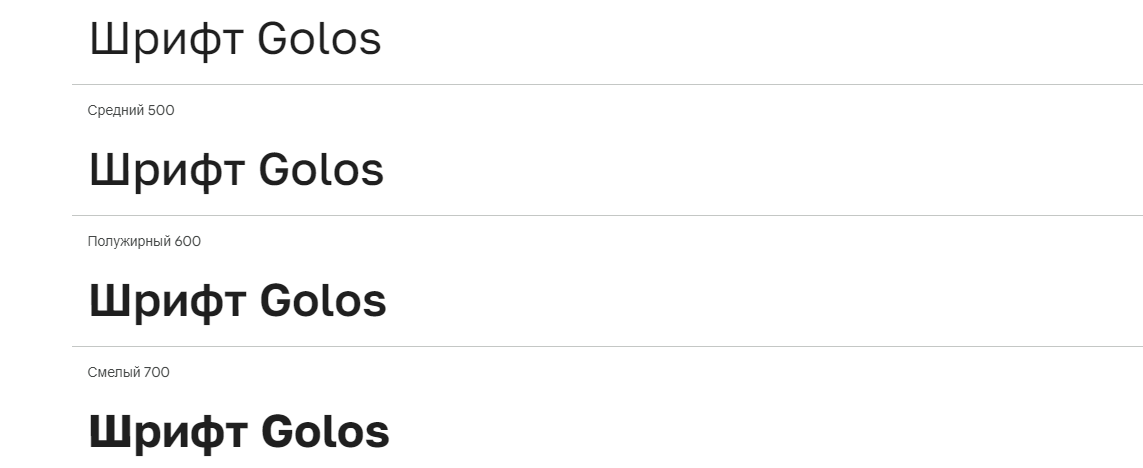
Arial, Times New Roman, Verdana и Tahoma — безопасны как fallback
Эти шрифты можно безопасно использовать в CSS-стеке как системные запасные варианты, если браузер берет их с устройства пользователя. Microsoft прямо пишет, что создатель сайта вправе указывать Windows-шрифты в font-family, потому что в таком случае шрифт используется на устройстве пользователя, а не на сервере сайта. Значит, конструкции вида Inter, Arial, sans-serif или Golos Text, Tahoma, sans-serif допустимы и не создают лицензионной проблемы сами по себе.
Практический вывод для безопасной зоны простой: если нужен минимальный риск, базовый веб-шрифт лучше брать из открытых гарнитур вроде Inter, Manrope или Golos Text, а Arial, Times New Roman, Verdana и Tahoma оставлять в роли системных fallback-шрифтов. Это наиболее устойчивая модель для российского сайта в 2026 году.
ШРИФТЫ С ЛИЦЕНЗИОННЫМИ РИСКАМИ
Лицензионный риск начинается там, где шрифт используют не так, как разрешает правообладатель. Для веба это особенно чувствительно, потому что публичное размещение файлов и встраивание шрифтов в сайт — отдельный режим использования, который далеко не всегда покрывается desktop-лицензией.
Arial, Times New Roman, Verdana и Tahoma — рискованы при self-hosting
Главная точка риска здесь не само название шрифта, а попытка превратить системный шрифт в webfont без отдельного права. Microsoft прямо указывает, что нельзя копировать Windows-шрифты на веб-сервер и нельзя самостоятельно конвертировать их в WOFF или WOFF2 для размещения на сайте. Поэтому если Arial, Times New Roman, Verdana или Tahoma используются как self-hosted webfonts, а не как локальные системные fallback-шрифты, это уже зона юридического риска.
Helvetica Now и другие коммерческие гарнитуры Monotype
Helvetica и Helvetica Now — не безопасный стандарт по умолчанию, а коммерческие гарнитуры Monotype. Monotype отдельно указывает, что для сайтов существует самостоятельный тип лицензии — webfont license. Следовательно, использование Helvetica на сайте требует не предположений, а подтвержденного права под конкретный сценарий. Если такой лицензии нет, веб-внедрение шрифта рискованно даже в том случае, если дизайнер привык считать Helvetica универсальной классикой.
Любые шрифты из непроверенных источников
Если файл шрифта скачан с сайта-агрегатора, из архива, из телеграм-канала или с форума, но у него нет ясной лицензии и понятного правообладателя, такой шрифт нельзя считать безопасным. Для сайта это особенно чувствительно, потому что публичное использование легче отслеживается, а претензии правообладателей чаще всего возникают именно в коммерческих и публичных кейсах.
Лицензионные риски возникают при self-hosting системных шрифтов, использовании коммерческих гарнитур без web-лицензии, загрузке файлов из непроверенных источников и самовольной модификации шрифтов. Санкционно-операционные риски для России связаны прежде всего с коммерческими шрифтами Monotype и сценариями, где для внедрения нужна новая покупка, продление лицензии, доступ к каталогу или постоянное сопровождение со стороны правообладателя.